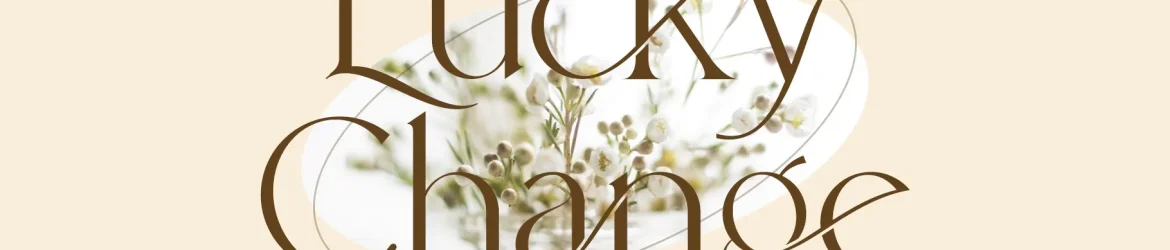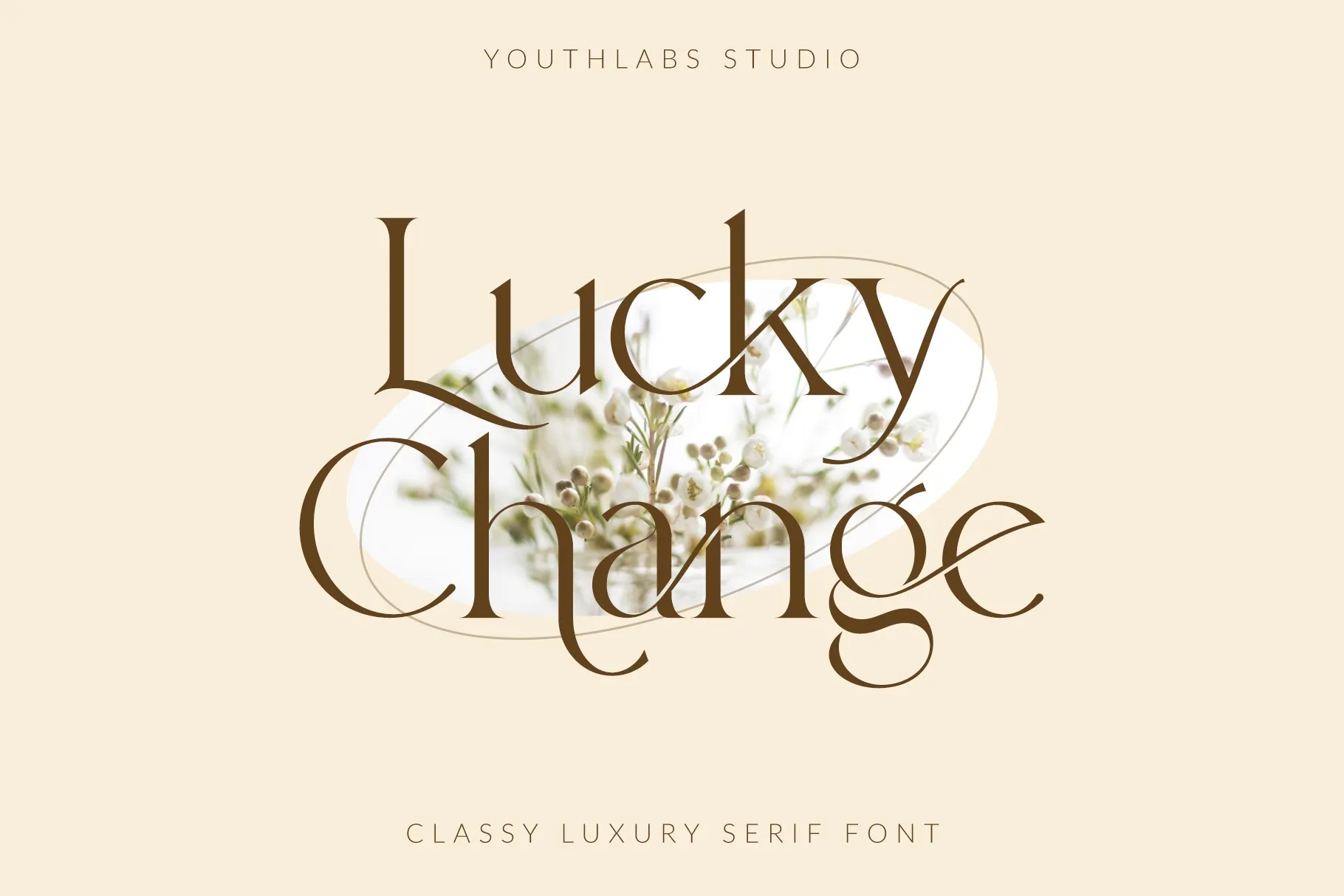
Lucky Change Font
Aqui está uma versão escrita para a descrição da página de download da font ‘Lucky Change Font’, adaptada ao tom solicitado: A ‘Lucky Change Font’ é uma elegante tipografia serif moderna, perfeitamente projetada para enfeitar qualquer projeto editorial ou design gráfico. Com um acabamento Premium e muitas feições Opentype que tornam a experiência de impressão ainda mais sofisticada e detalhada, essa fonte irá conferir ao seu material um toque de classe. Se você busca uma fonte para dar vida à sua ideia, sem perder o clima de elegância característico do design serif tradicional, ‘Lucky Change Font’ é a escolha perfeita. Suas linhas elegantes e suas curvas suaves garantem que seu texto fique ainda mais impecável. Ideal para editoriais, publicações profissionais ou até mesmo para criar gráficos de marketing inovadores, esta fonte 99designs é a opção perfeita para qualquer designer que busca um acabamento sofisticado e moderno em seus projetos.